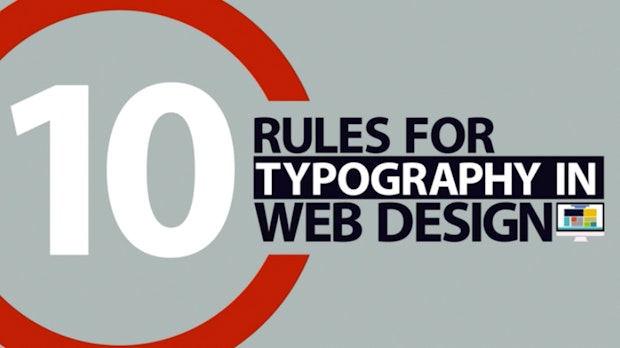
Typografie-Regeln im Web-Design: Youtube-Video zeigt, worauf du achten solltest
Dieses kurzweilige Youtube-Video beschäftigt sich mit Typografie-Regeln im Web-Design. Super geeignet für eine kleine Wissensauffrischung.
Typografie-Regeln im Web-Design. (Screenshot: Youtube)
Egal ob du ein Neueinsteiger oder ein Profi im Bereich des Web-Designs bist – es ist gut und wichtig, alles über Typografie zu wissen, was du in die Finger bekommen kannst. Die bevorzugte Schriftart ist immerhin eines der Aushängeschilder auf Webseiten, und sie sollte gut durchdacht und gewählt sein.
In einem Video des Logo-Design-Guru-Blogs haben sich Experten zehn essenzielle Regeln überlegt, die Interessierte beim Thema Typografie im Web-Design beachten sollten. Der zweiminütige Clip rät beispielsweise dazu, den Lorem-Ipsum-Text in bestimmten Situationen wegzulassen und immer responsive Typografie zu nutzen.